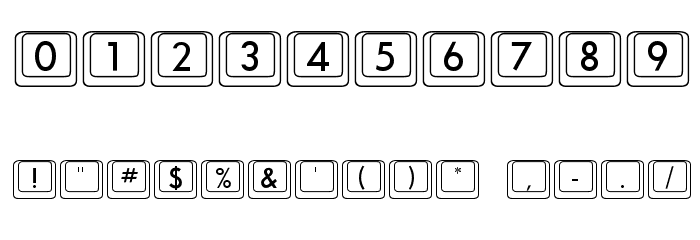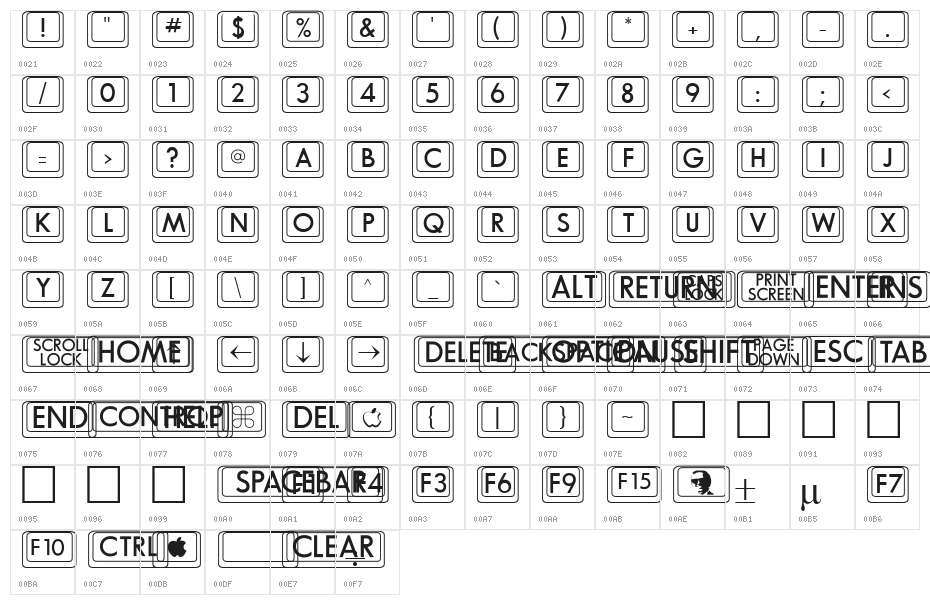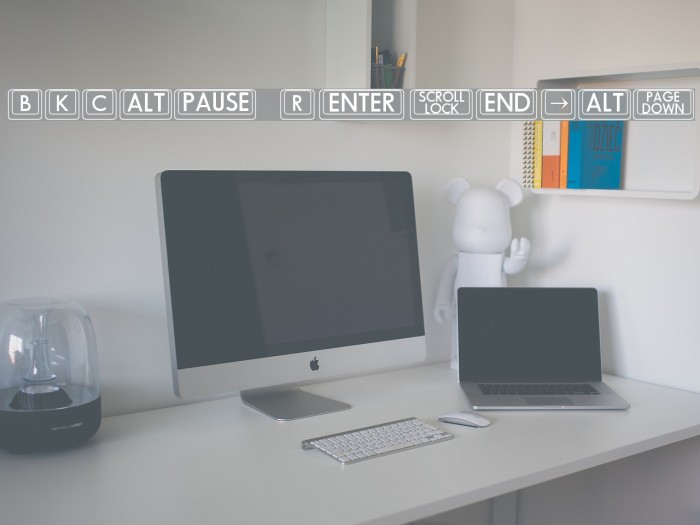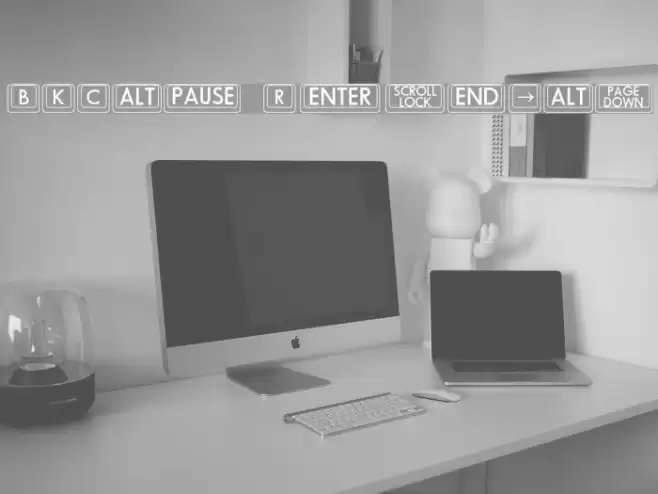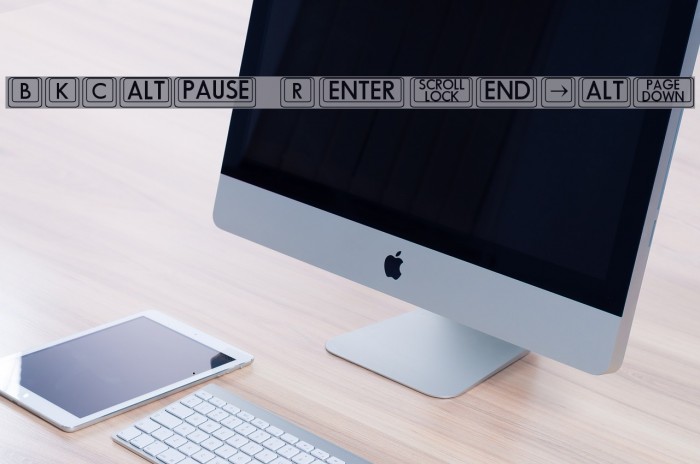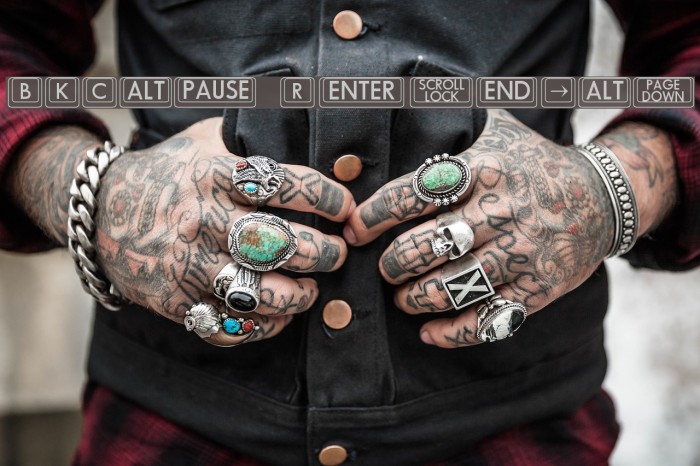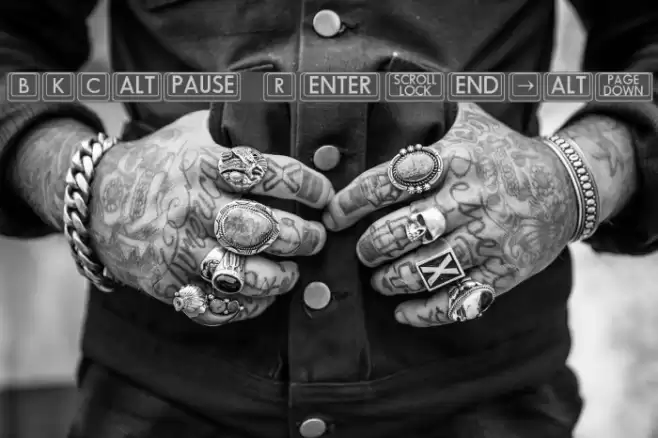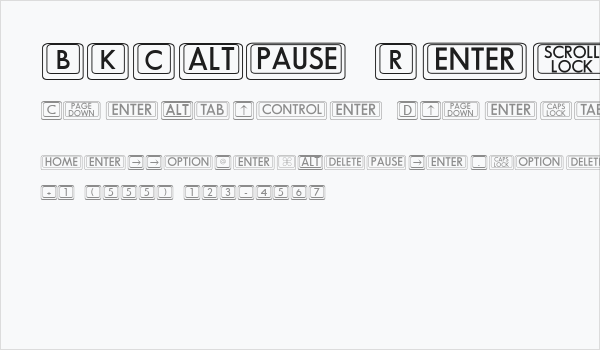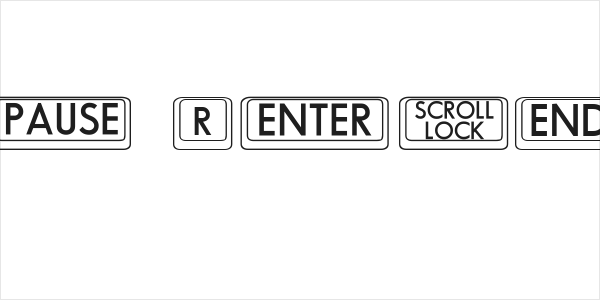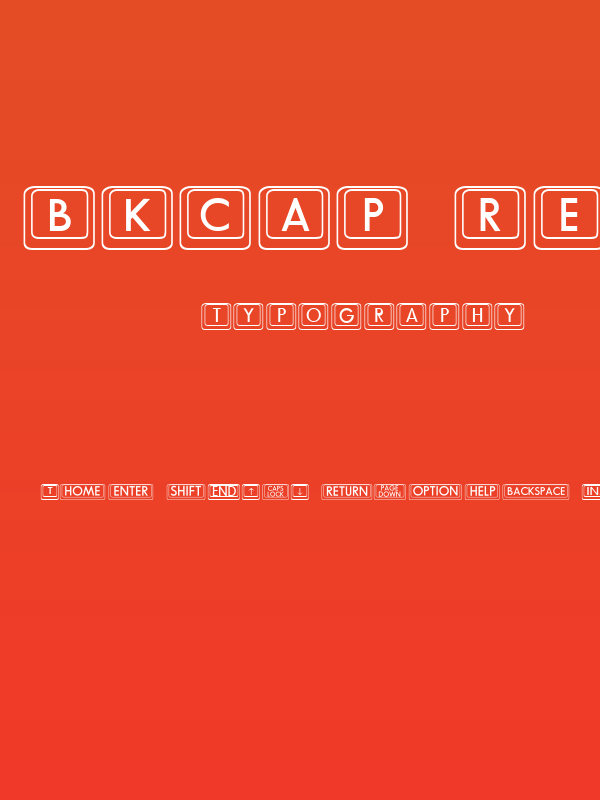
BKCap Regular Font
Fonts by David Rakowski
| Proiecte propuse | Ideal for retro-themed designs, tech-related projects, or any creative work that seeks to evoke a sense of nostalgia. |